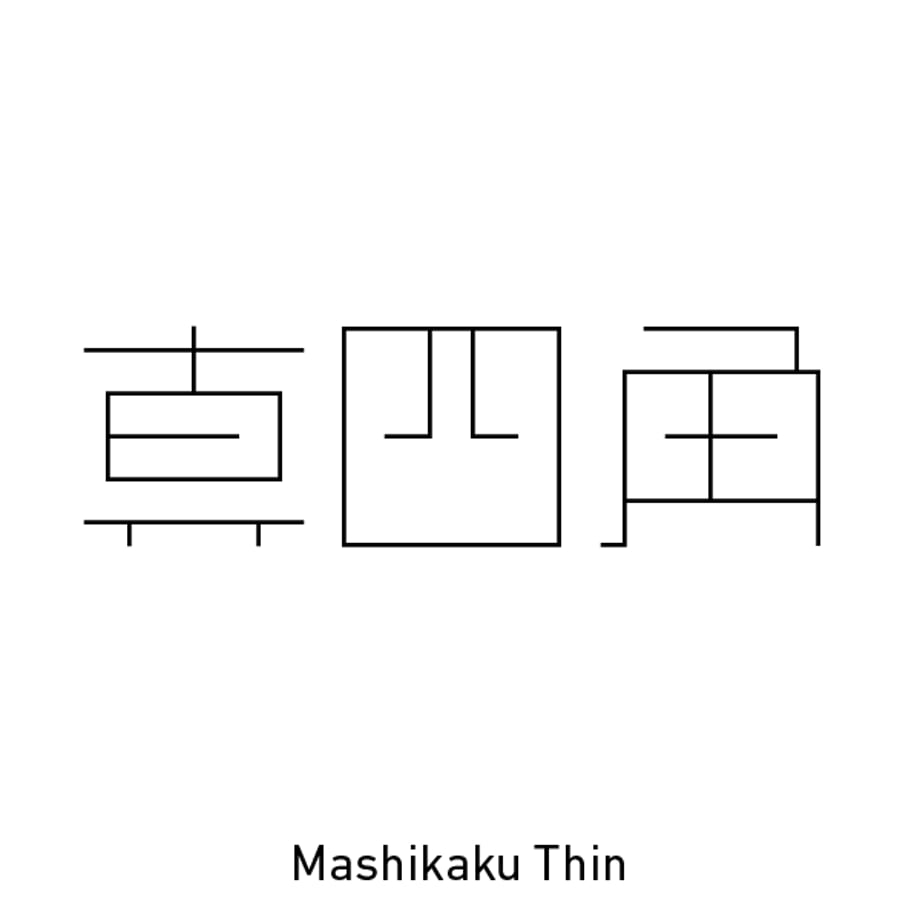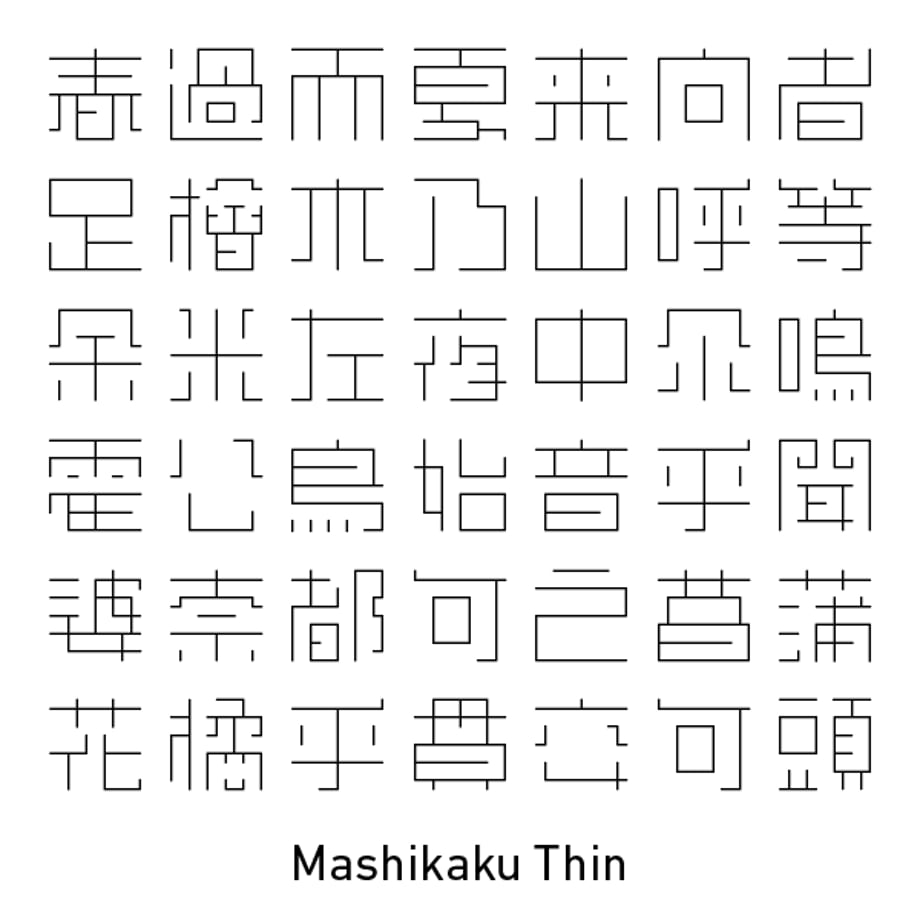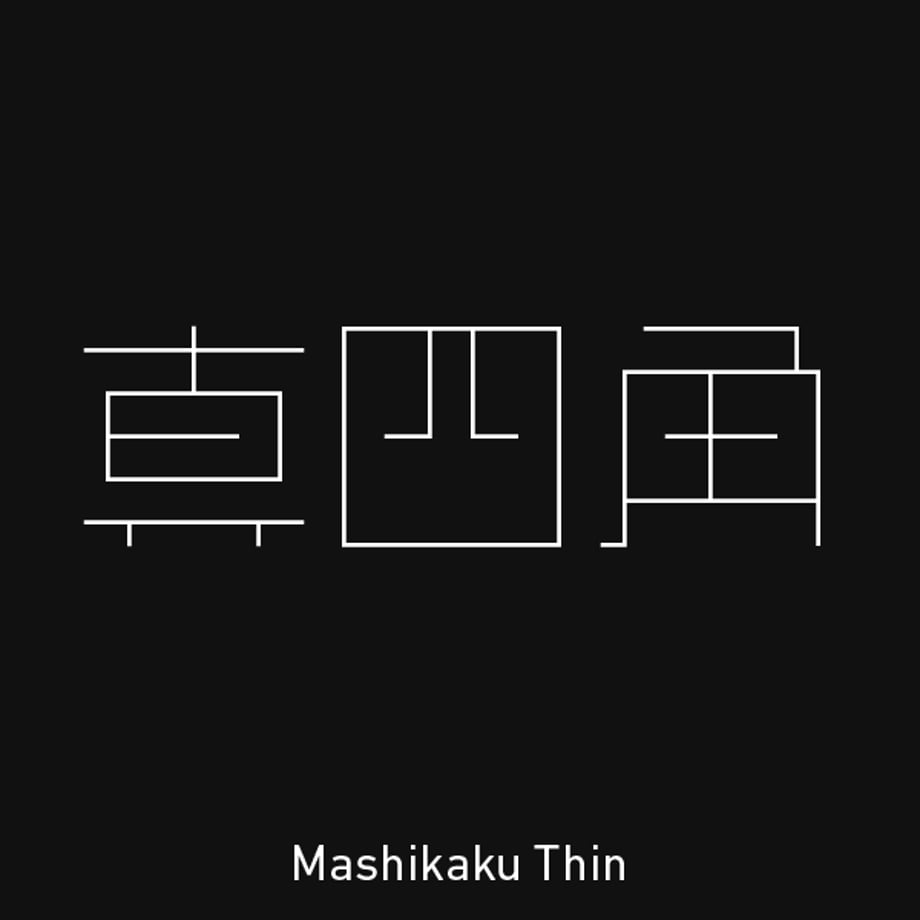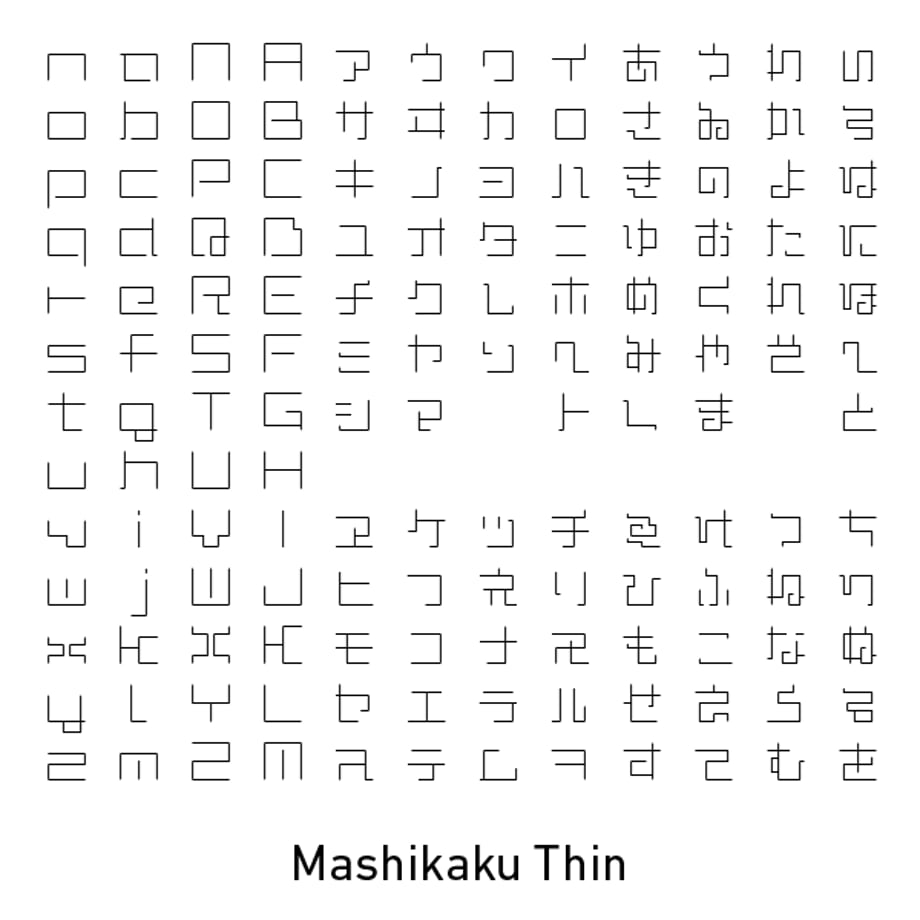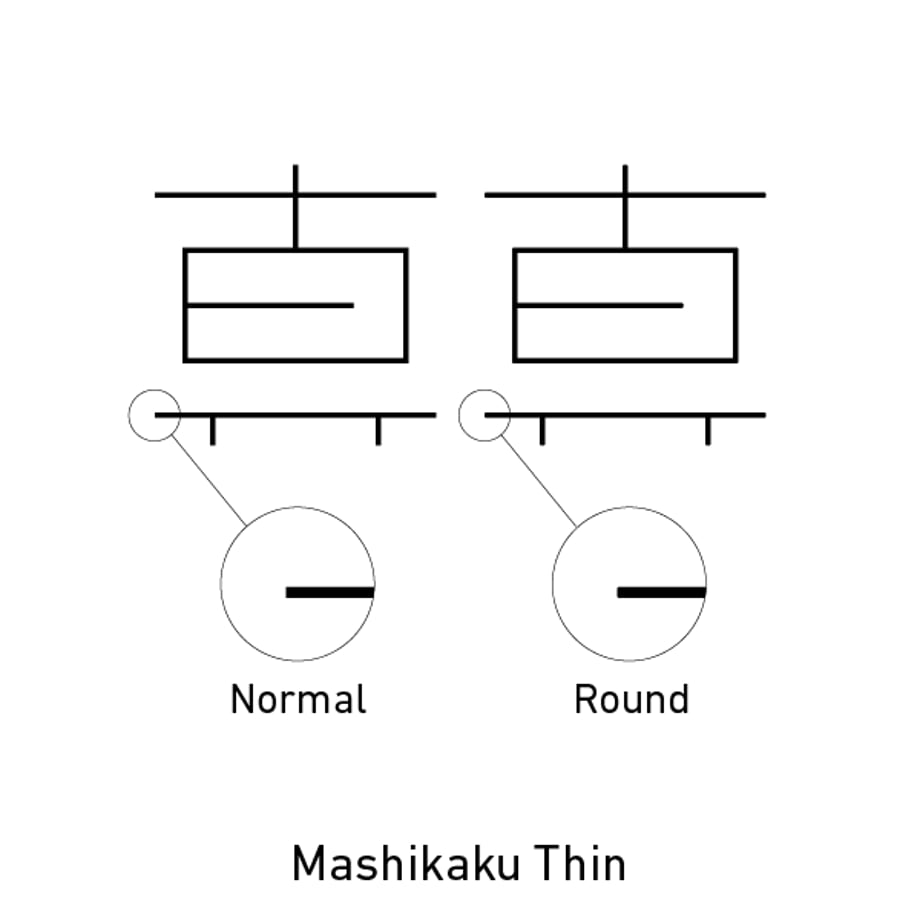
真四角書体 CJK(Mashikaku CJK)- Thin
真四角書体は、江戸文字「角字」にインスパイアされています。正方形の中に水平・垂直の線のみで構成される図形的なスタイルを踏襲しながら、現代の生活空間に自然となじむようにシンプルで親しみやすいデザインの書体です。
2026年3月のver.5(CJK Edition)アップデートでは、収録漢字を約22,000字に拡充し、9種類のウェイト展開に進化。日常利用からプロフェッショナルな制作まで、幅広くお使いいただけます。
■アップデート内容(ver.5/CJK Edition)
・漢字の文字数が大幅増量。約22,000字(※1)
・日本語書体の字体・字形をベースにした「CJK統合漢字(20,992字)」、JIS X 0213の漢字(第1〜第4水準)を収録
・ウェイトの見直し。ウェイト9種類に増加
スタイル:Normal(スクエア), Round(ラウンド/角丸)の2種を同梱
■バリエーション